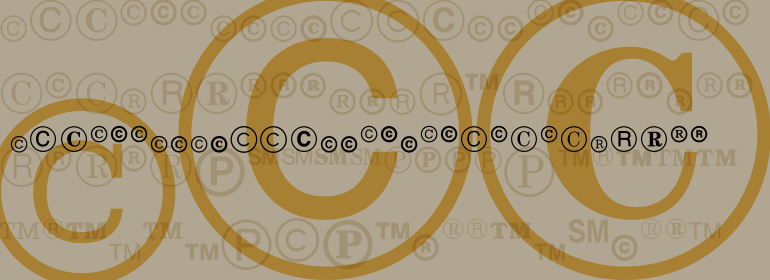
Legal Trademarks
Legal Trademarks,这款字体结构工整、笔画清晰,兼顾美观与易读性,适用于标题、正文、海报、包装、LOGO 等多种场景。字形优雅稳定,风格百搭耐看,适配日常排版与创意设计,让文字呈现更舒适、更具质感。Legal Trademarks一笔一画,皆是细节,以均衡的比例、流畅的线条打造舒适视觉体验,字形端正大气,风格简约现代。无论是商业设计、品牌宣传还是日常排版,都能轻松驾驭,让文字更有格调与力量。Legal Trademarks字体下载。